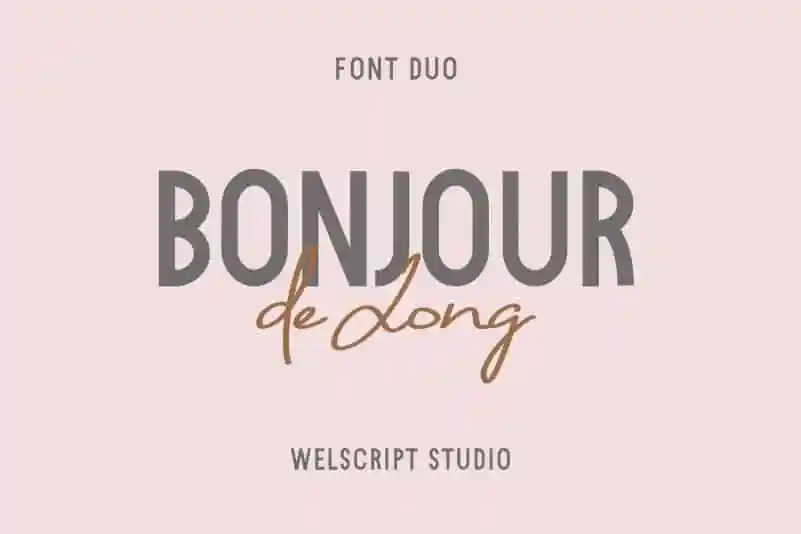
Bonjour de Jong Font Duo – Download Grátis
Bonjour de Jong Font Duo é uma dupla de fontes modernas e incrivelmente bela que se destaca para criar logos impactantes, panfletos elegantes, cartões de casamento sofisticados, posts de blog atraentes e postagens nas redes sociais chamativas. Esta família de fontes vem em versão gêser clássica e extrema, oferecendo uma ampla paleta de opções para designers buscando trazer um toque único e moderno a seus projetos digitais. Com um design minimalista e elegante, esta dupla de fontes é perfeita para quem busca estilizar suas ideias de forma sofisticada, independentemente do formato ou plataforma da publicação. Seja no ambiente digital ou impresso, Bonjour de Jong Font Duo pode transformar qualquer projeto em uma obra de arte gráfica.